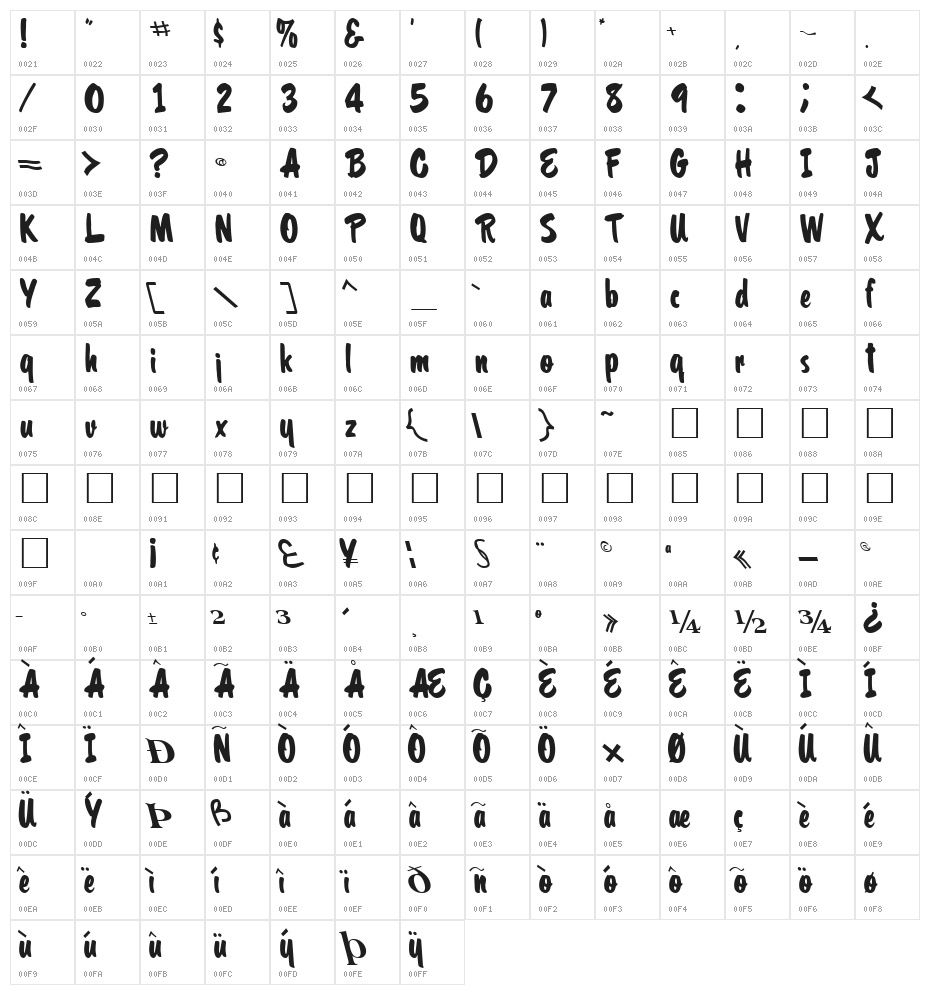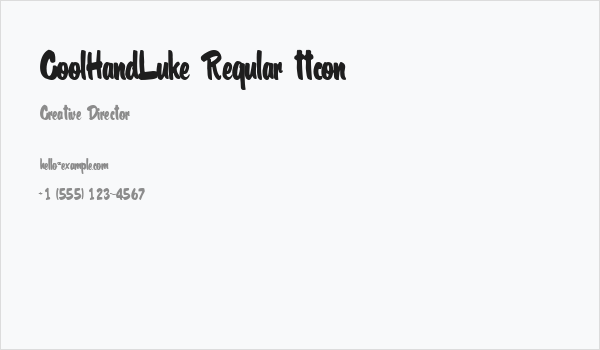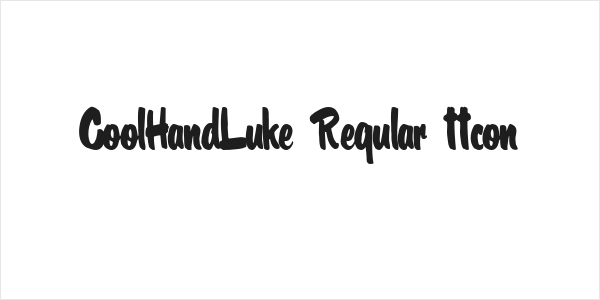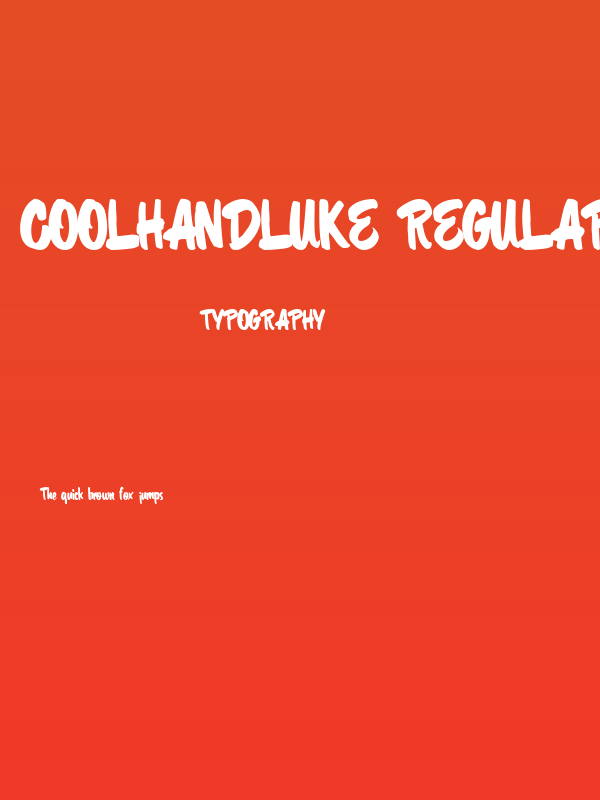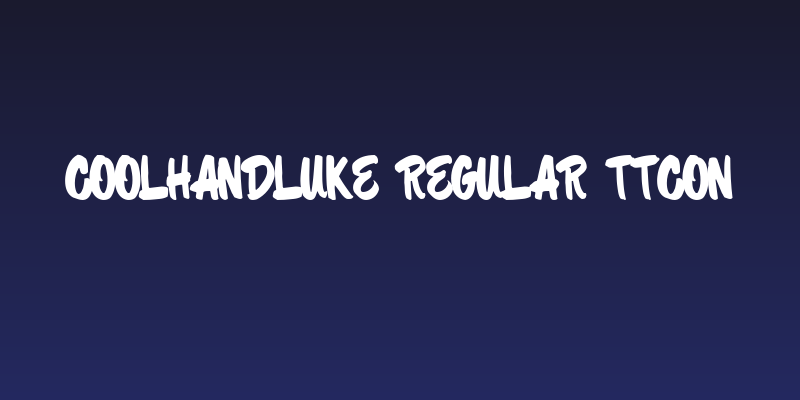
CoolHandLuke Regular ttcon Font
| Stile generale | Playful, Casual |
| Progetti proposti | Ideal for projects that require a personal touch, such as greeting cards, posters, or branding for creative businesses. |